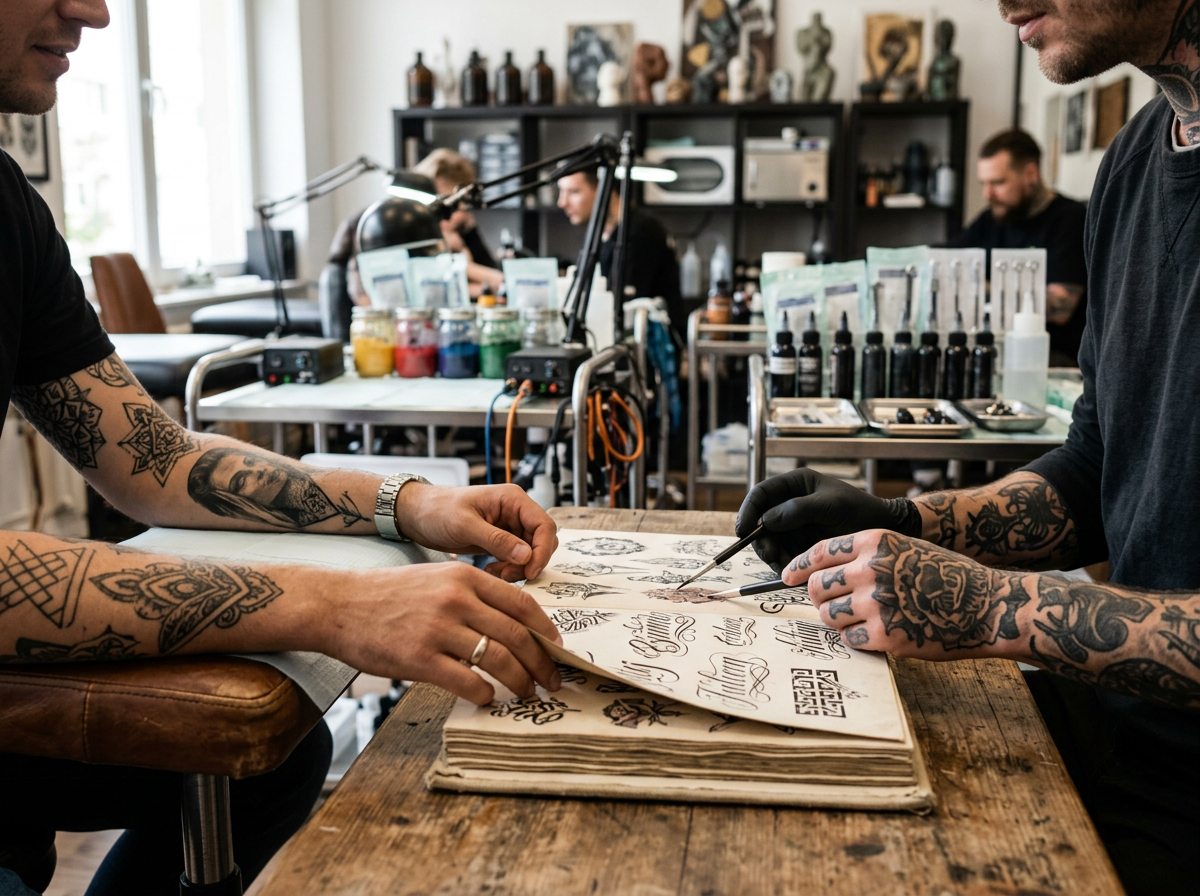
Schriftarten für Tattoos: Hintergründe und praktische Hinweise zur Auswahl
Ein Tattoo ist mehr als nur Tinte unter der Haut; es ist eine dauerhafte Botschaft, ein Statement oder eine Erinnerung. Die Auswahl der richtigen Schriftart spielt dabei eine entscheidende Rolle, denn sie prägt die gesamte Wirkung des Motivs maßgeblich. Eine unpassende Typografie kann die Aussagekraft mindern oder die Lesbarkeit auf lange Sicht beeinträchtigen.
Viele Menschen unterschätzen die Komplexität hinter der Wahl der passenden Schrift. sehen nur das Design, nicht die feinen Linien, die Alterung der Haut oder die spezifischen Anforderungen des Tätowierprozesses. Ein scheinbar perfekter Font auf dem Bildschirm kann auf der Haut schnell zu einer unleserlichen Masse verschwimmen.
Dieser Leitfaden beleuchtet die wichtigsten Aspekte bei der Entscheidung für eine Tattoo-Schriftart. Er zeigt, welche Faktoren die Ästhetik und Haltbarkeit beeinflussen und wie sich mit fundiertem Wissen die optimale Wahl treffen lässt, um ein dauerhaft ansprechendes Ergebnis zu erzielen.
Kurz zusammengefasst
- Die Schriftart beeinflusst die Wirkung und Lesbarkeit eines Tattoos nachhaltig.
- Feine Linien und zu enge Abstände können auf der Haut verschwimmen.
- Klassische Stile wie Serifen- und Sans-Serif-Schriften bieten gute Haltbarkeit.
- Die Platzierung am Körper und die Hautbeschaffenheit sind entscheidende Faktoren.
Welche Schriftarten eignen sich besonders gut für dauerhafte Hautmotive?
Für dauerhafte Hautmotive eignen sich besonders gut Schriftarten, die eine klare Lesbarkeit und eine gewisse Robustheit aufweisen, da die Tinte unter der Haut im Laufe der Zeit leicht verlaufen kann und feine Details verschwimmen. Klassische Serifen- und Sans-Serif-Schriften sind hier oft die beste Wahl, da die Struktur auch nach Jahren noch gut erkennbar bleibt.
Die Auswahl einer geeigneten Typografie für ein Tattoo erfordert Weitsicht. Viele moderne, filigrane Schriften, die auf Papier oder Bildschirmen beeindrucken, verlieren auf der Haut die Kontur. Das liegt an der natürlichen Regeneration der Hautzellen und der Ausbreitung der Pigmente im Laufe der Jahre.
Klassische Serifen-Schriften: Zeitlose Eleganz
Serifen-Schriften, erkennbar an den kleinen Füßchen an den Buchstabenenden, strahlen eine traditionelle und oft elegante Ästhetik aus. bieten eine gute Lesbarkeit, da die Serifen das Auge beim Lesen führen.
Beispiele hierfür sind die bekannten Times New Roman oder Georgia, die sich durch die klare Struktur auszeichnen. Diese Schriften eignen sich hervorragend für längere Textpassagen oder Namen, wo die Lesbarkeit im Vordergrund steht.
Die Strichstärke spielt eine wichtige Rolle. Zu dünne Serifen können mit der Zeit verschwimmen, während kräftigere Varianten die Form besser behalten. Ein erfahrener Tätowierer wird hierzu fundierte Empfehlungen aussprechen können.
Moderne Sans-Serif-Schriften: Klare und schnörkellose Optik
Sans-Serif-Schriften, also Schriften ohne Serifen, wirken modern, geradlinig und minimalistisch. die klare Formgebung ohne zusätzliche Verzierungen macht sie besonders unempfindlich gegenüber dem natürlichen Alterungsprozess der Haut.
Beliebte Beispiele sind Helvetica, Arial oder Open Sans. Diese Schriften eignen sich für eine Vielzahl von Motiven, von einzelnen Wörtern bis hin zu kurzen Zitaten. die Schlichtheit sorgt für eine ausgezeichnete Lesbarkeit, selbst aus größerer Entfernung.
Bei der Wahl einer Sans-Serif-Schrift ist auf eine ausreichende Strichstärke zu achten. Extrem dünne Varianten können ebenfalls problematisch werden, da sie anfälliger für das Verblassen und Verschwimmen sind als kräftigere Ausführungen.
Kurz gesagt: Robuste Serifen- und Sans-Serif-Schriften mit ausreichender Strichstärke sind ideal für Tattoos, da sie auch nach Jahren die Lesbarkeit bewahren.
Wie beeinflusst die Strichstärke die Haltbarkeit eines Tattoo-Textes?
Die Strichstärke beeinflusst die Haltbarkeit eines Tattoo-Textes maßgeblich, da zu feine Linien im Laufe der Zeit durch die natürliche Ausbreitung der Tinte unter der Haut verschwimmen oder sogar vollständig verschwinden können. Kräftigere Linien behalten die Kontur deutlich länger und bleiben somit besser lesbar.
Ein häufiger Fehler bei der Planung eines Schriftzug-Tattoos ist die Unterschätzung der biologischen Prozesse der Haut. Die Dermis, die Hautschicht, in die die Tinte eingebracht wird, ist kein statisches Medium. Pigmente können sich dort mit den Jahren leicht ausbreiten, ein Phänomen, das als „Blowout“ oder „Verlauf“ bekannt ist.
Die Gefahr feiner Linien und enger Abstände
Besonders bei filigranen Schriften mit sehr dünnen Linien und engen Buchstabenabständen ist das Risiko des Verschwimmens hoch. Was auf dem Entwurf scharf und präzise aussieht, kann auf der Haut schnell zu einem unleserlichen Fleck werden.
Ein Beispiel hierfür sind Schriften im „Fine Line“-Stil. Obwohl ästhetisch ansprechend, erfordern sie eine extrem präzise Ausführung und sind anfälliger für altersbedingte Veränderungen. Die feinen Linien können sich überlappen und die Buchstaben unkenntlich machen.
Letztlich ist die Zusammenarbeit mit einem erfahrenen Tätowierer der Schlüssel zum Erfolg. Seine Expertise in der Anpassung der Schrift an die individuelle Körperanatomie und die Hautbeschaffenheit ist unersetzlich. Nur so lässt sich sicherstellen, dass die gewählte Schriftart nicht nur heute, sondern auch in vielen Jahren noch die volle Wirkung entfaltet und die gewünschte Botschaft klar vermittelt.